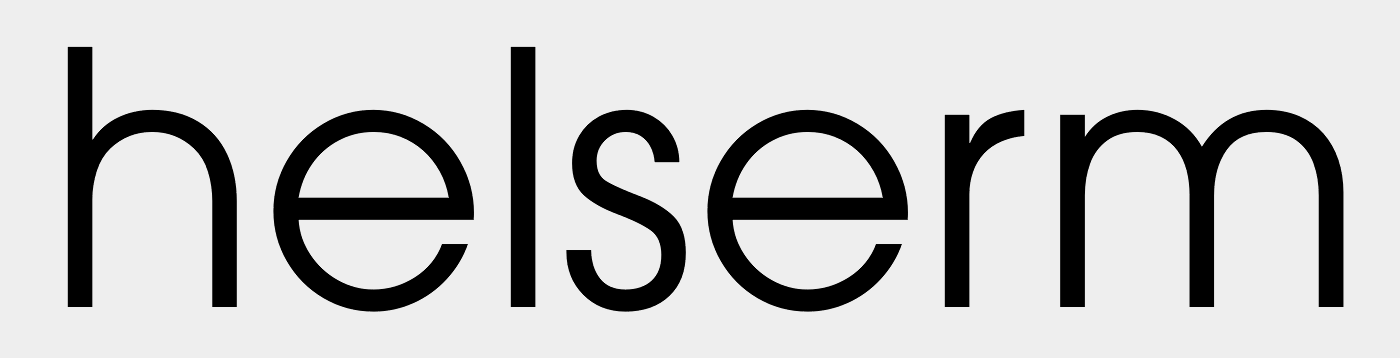
Suche Schriftart von "helmers"
ich bin auf der Suche nach der Schriftart von "helmers"
Century Gothic kommt nahe ran, ist es aber nicht ganz genau.
Kann mir jemand helfen?
Das komische r ist so im Freefont "Decker" enthalten. Nimm aber lieber das Original.
Die ITC Avant Garde Book passt perfekt!!!